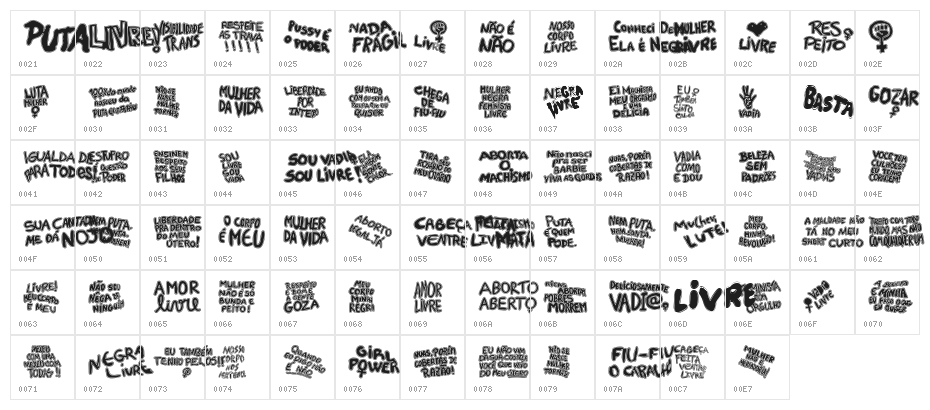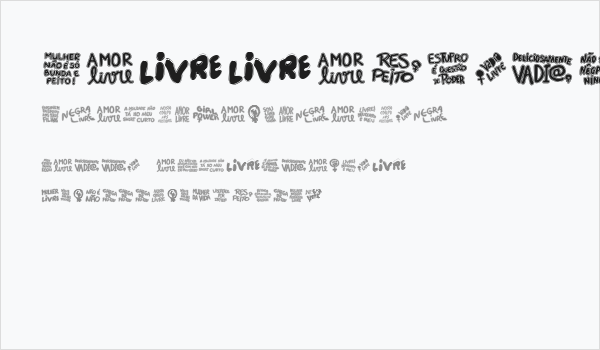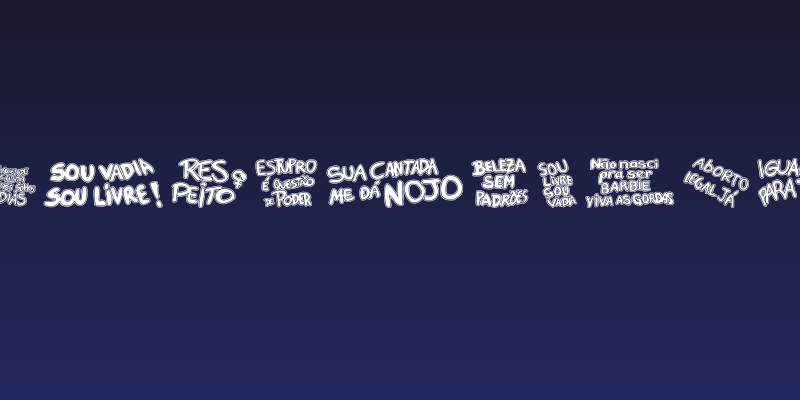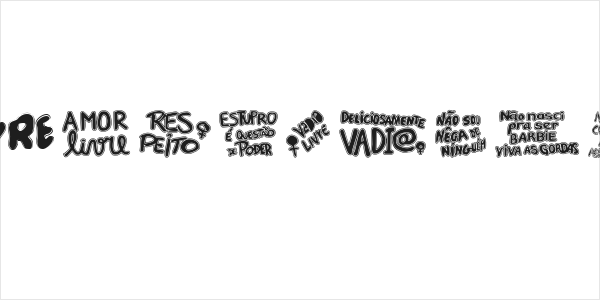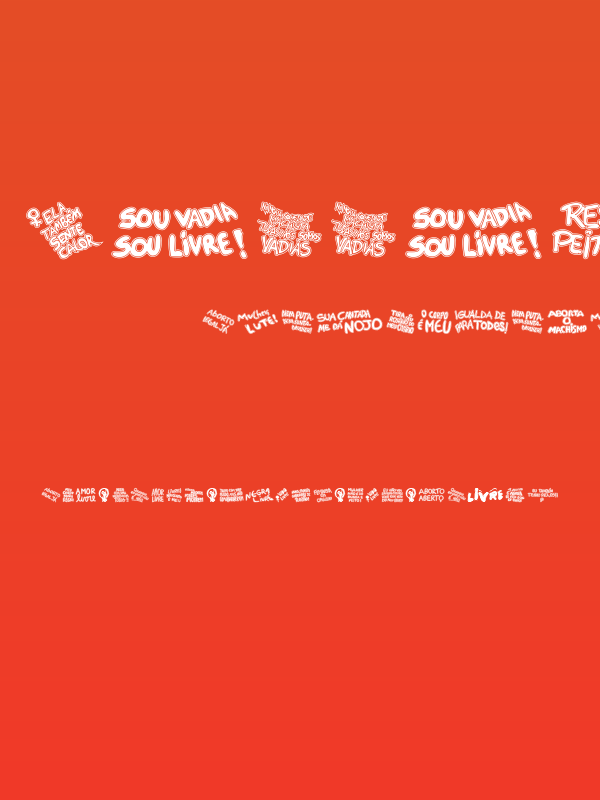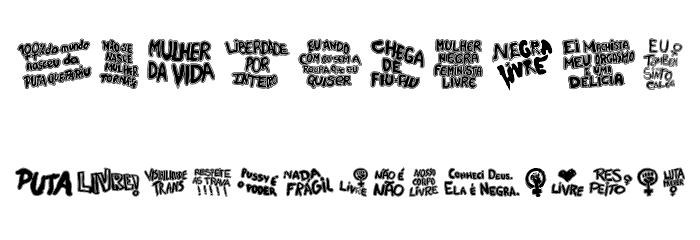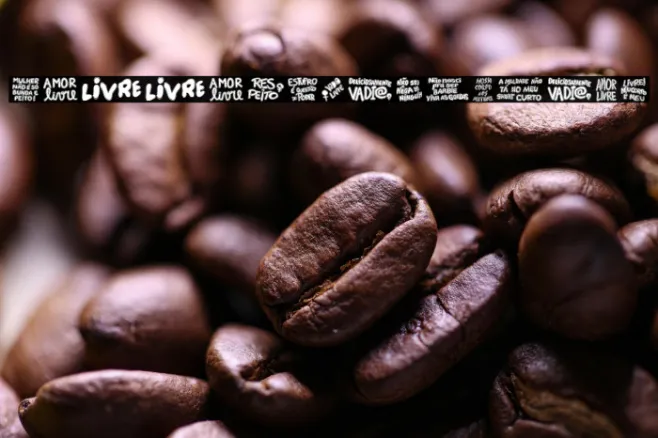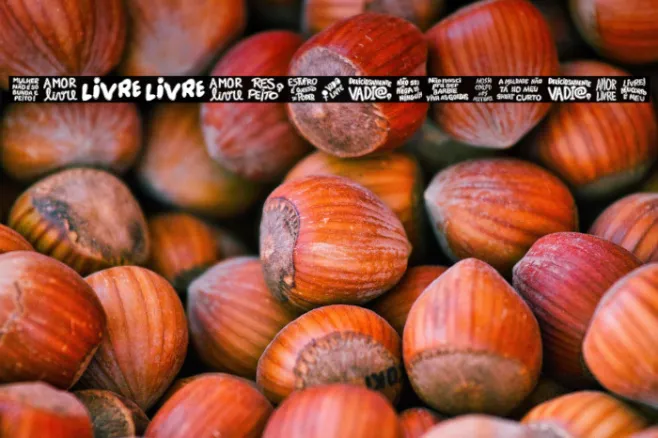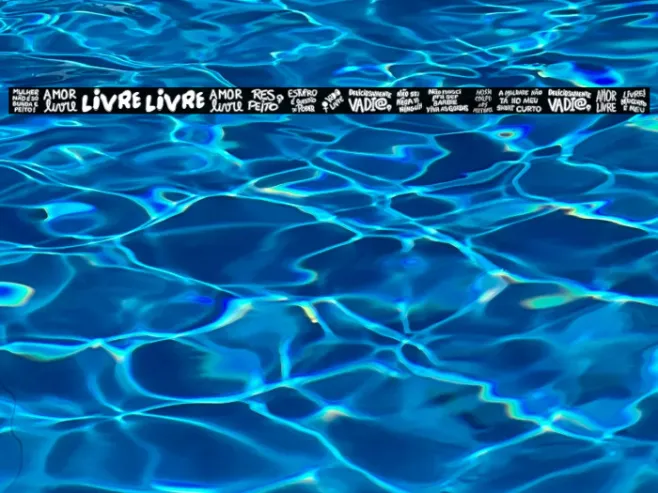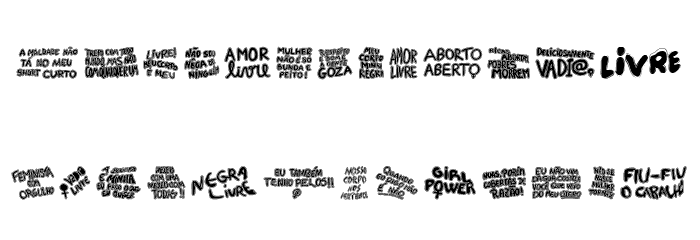
femme-BoldItalic Font
| Style général | Modern, Artistic |
| Cas d'utilisation | Headlines, Posters, Artistic Designs |
| Projets proposés | Ideal for posters, protest signs, artistic projects, and any design requiring a bold, expressive typeface. |